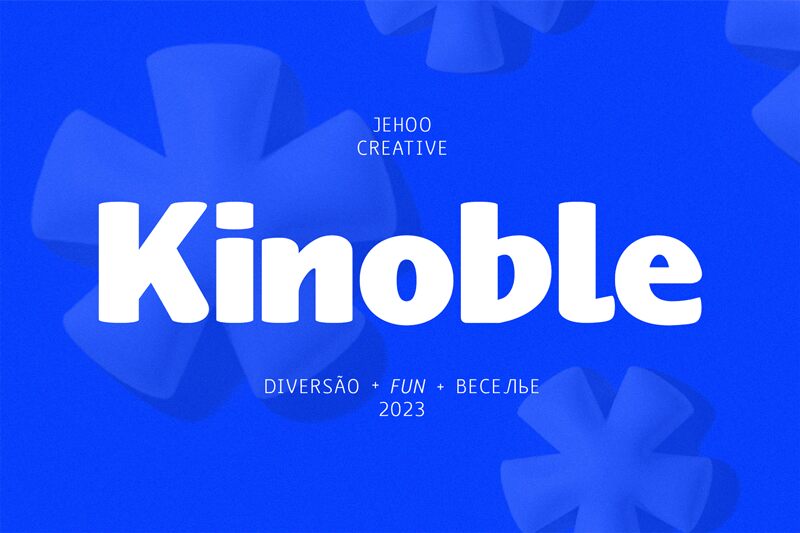
Kinoble, da Jehoo Creative, é uma fonte sem serifa arredondada e gratuita, com uma personalidade geométrica suave e um toque contemporâneo e sereno. As letras combinam curvas largas e abertas com formas de lados retos, garantindo que a fonte pareça amigável sem parecer infantil ou excessiva.
É perfeita para branding, gráficos de aplicativos, embalagens, títulos de cartazes e cabeçalhos em redes sociais onde você deseja formas limpas com um toque de calor humano. Sendo uma fonte gratuita, Kinoble também funciona muito bem para títulos editoriais curtos ou logotipos simples, pois suas formas redondas e suaves mantêm o texto breve com uma aparência equilibrada e composta.